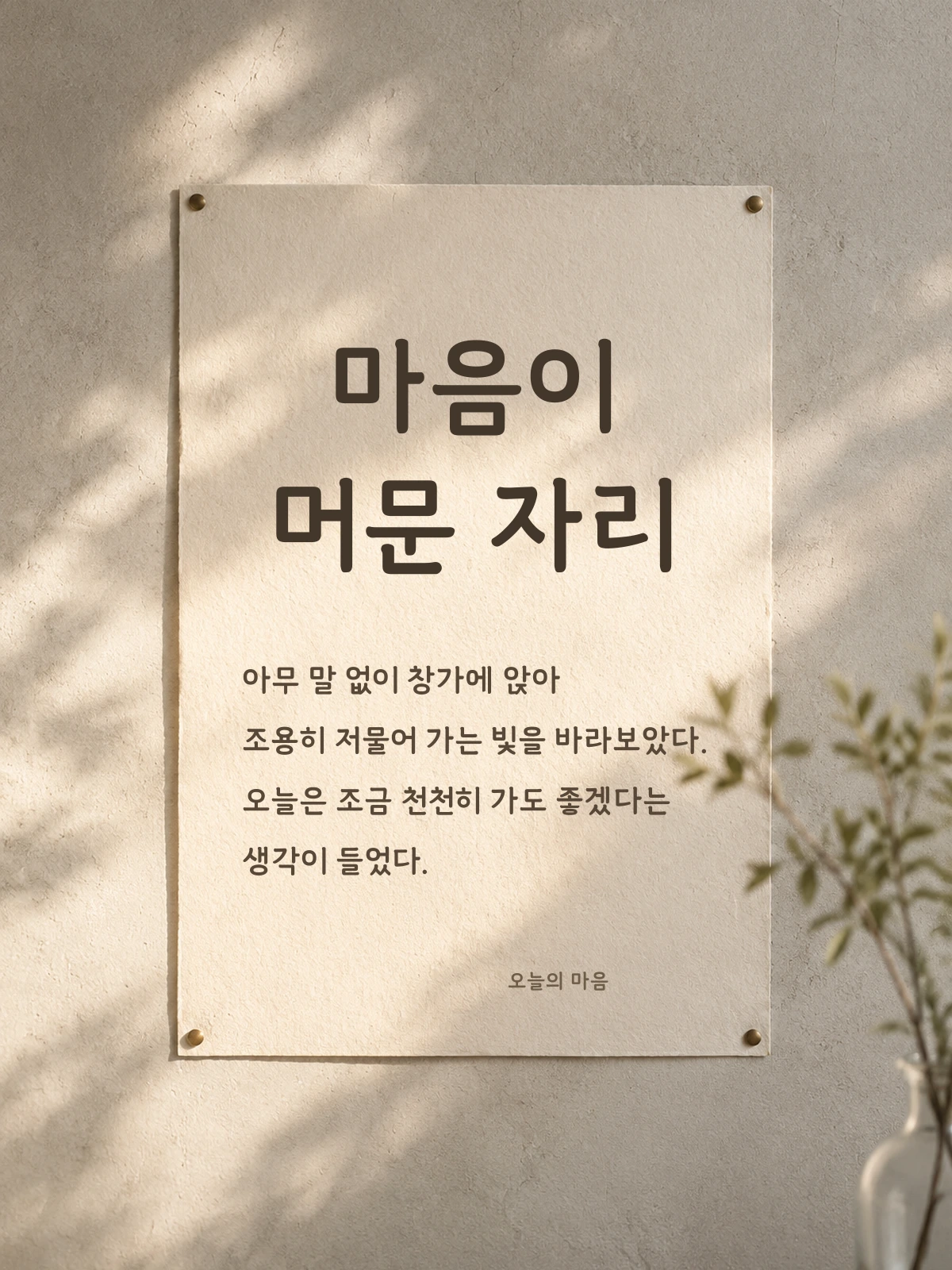
갬성명조 — (주)와이즈폰트에서 배포하는 무료 폰트입니다. 명조의 단정한 골격에 손글씨 특유의 자연스러운 획을 더한 감성적인 손글
이름을 먼저 짚고 넘어가야 하는 서체입니다. 명조라는 이름이 붙어 있지만 파일을 열어 보면 획 끝에 부리가 없습니다. 세로획이 가로획보다 3할쯤 굵어 약간의 대비는 있지만, 전형적인 명조가 보이는 1.7배 이상의 대비에는 크게 못 미칩니다. 부리 없는 민부리에 굵기 변화를 살짝 준 형태에 가깝습니다.
그래서 인상은 명조의 격식보다 손글씨의 부드러움 쪽입니다. 받침이 붙어도 높이가 거의 변하지 않는 네모틀이고 낱자는 정사각형에 가까워, 손글씨 계열치고는 글줄이 가지런하게 떨어집니다.
명조를 찾다가 이 서체를 고르시는 거라면 기대와 다를 수 있습니다. 반대로 부드럽고 감성적인 인상의 서체를 찾는 자리라면 잘 맞습니다. 현대 한글 11,172자를 모두 담았고 굵기는 하나입니다.